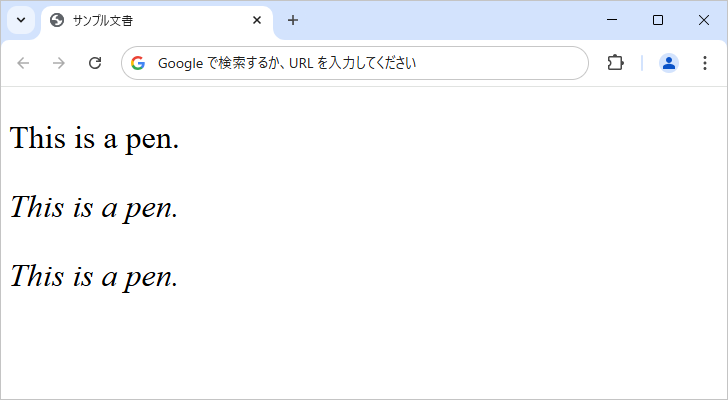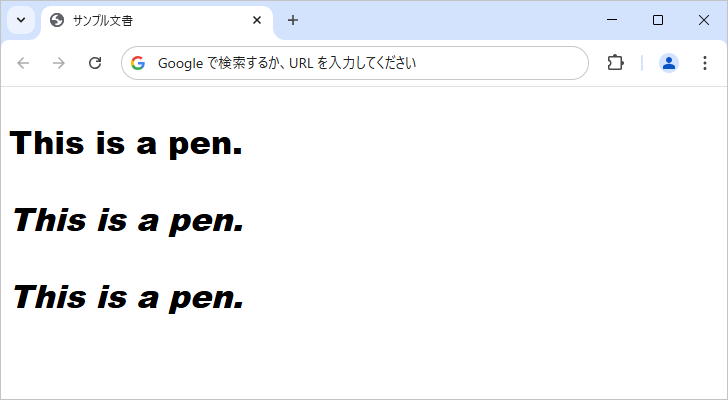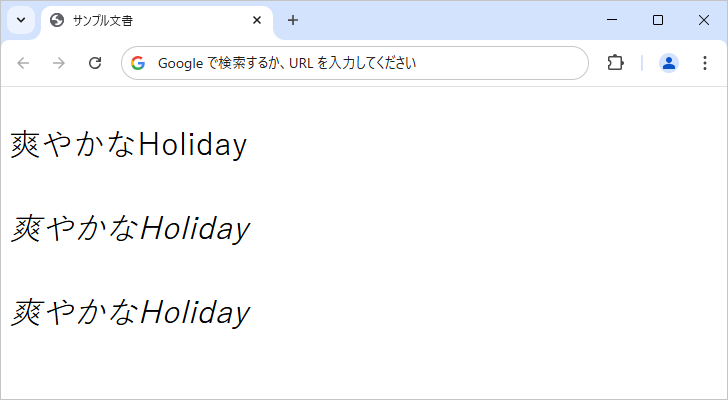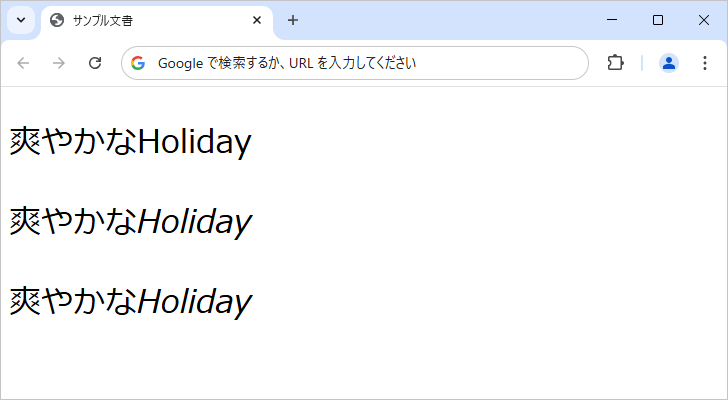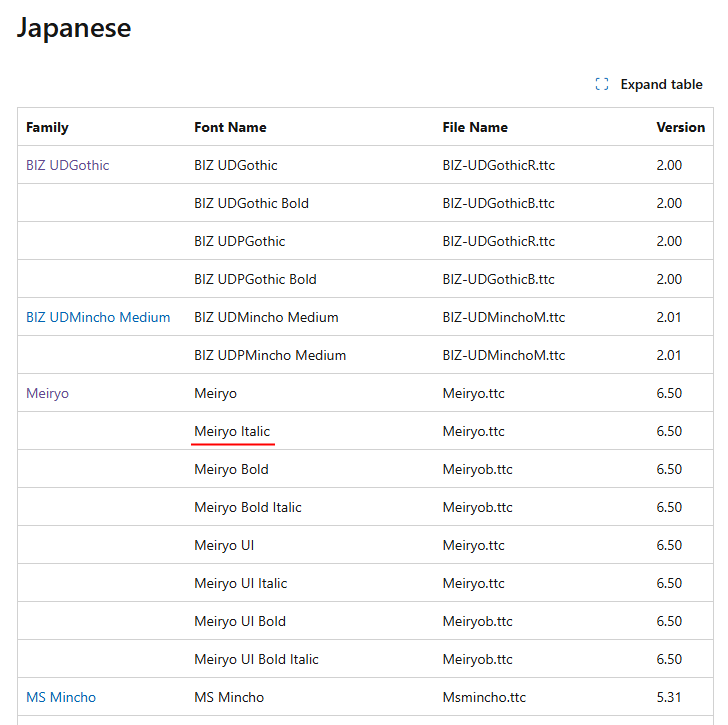
フォントのスタイルを設定する
Web ページで表示されるテキストのフォントのスタイルを設定するには、CSS の font-style プロパティを使用します。このプロパティを使うことで、テキストのスタイルを normal(標準)、 italic(イタリック体)、 oblique(斜体)のいずれかに設定できます。イタリック体( italic )は、フォントにイタリック専用のデザインがある場合に適用され、より自然なスタイルになります。一方、斜体( oblique )は、フォントにイタリックスタイルがない場合に、通常のフォントを人工的に傾けて表示します。この記事では Web ページのテキストに適用するフォントスタイルの設定方法について詳しく解説します。
font-styleを使ってフォントのスタイルを設定する
フォントのスタイルを設定するには CSS の font-style プロパティを使用します。書式は次の通りです。
スタイルには次の 3 つのいずれかを設定します。
説明
normal標準のフォントで表示
italicイタリック体のフォントで表示
oblique斜体のフォントで表示
font-style プロパティに normal を設定した場合は、標準のフォントで表示されます。 italic を設定した場合、そのフォントに イタリック体が用意されている場合は、それが適用されます。 oblique を設定した場合、そのフォントに斜体がある場合は、それが適用されます。ただし、多くのフォントは oblique スタイルを持っておらず、代わりに italic スタイルが適用されることが一般的です。対象のフォントがイタリック体も斜体も持っていない場合は、標準のフォントをブラウザが人工的に傾けた状態(擬似的な斜体)にして表示します。
なお font-style プロパティの初期値は normal です。
例えば p 要素に対してフォントのスタイルとして italic を設定する場合は次のように記述します。
簡単なテストとして次のような HTML 文書を作成しました。複数の p 要素に対してそれぞれ異なるフォントのスタイルを設定しています。
3 つの p 要素に対してそれぞれフォントのスタイルとして、 normal 、 italic 、 oblique を設定しました。 p 要素に表示されているテキストのフォントのスタイルが変更されていることが確認できます。
font-styleを使ってフォントのスタイルを設定する(1)
今回の場合、スタイルとして italic と oblique のどちらを設定した場合も同じ表示となっています。この理由は後述します。
イタリック体と斜体の違いについて
フォントのスタイルを設定するとき、 italic を設定するとフォントが持っているイタリック体、 oblique を設定するとフォントが持っている斜体、もしくは機械的に傾けたフォントが使用されます。
italic は、フォントデザインの段階で作成された専用のイタリック体を使用します。 oblique は、フォントに斜体がある場合はその斜体が適用され、ない場合はイタリック体があればイタリック体を代用し、イタリック体もない場合は標準フォントを機械的に傾けて表示します。
例えば、フォントとして Times New Roman を使用した場合、 italic を設定すると Times New Roman Italic が適用されます。一方で oblique を設定しても、 Times New Roman には Oblique スタイルが存在しないため、イタリック体が代用されます。
先ほどのサンプルではフォントとして Times New Roman を使用しました。 Times New Roman はイタリック体が用意されています。ブラウザに表示された a の文字をみてください。
イタリック体と斜体の違いについて(1)
標準のフォントとイタリック体のフォントでまったく異なる文字の形をしていることが分かります。このようにイタリック体で表示する場合は、イタリック体を使って表示します。なお Times New Roman には斜体がありません。このようにイタリック体はあるけれど斜体がない場合はイタリック体を使用して表示します。先ほどのサンプルでイタリック体と斜体が同じ表示になっていたのはこのためです。
イタリック体も斜体も用意されていない場合
イタリック体も斜体も用意されていない場合に、フォントのスタイルとして italic や oblique を設定すると、標準のフォントをブラウザが人工的に傾けた状態(擬似的な斜体)にして表示します。
例えば Windows11 の環境だと Arial Black にはイタリック体も斜体も用意されていません。そこでフォントの種類として Arial Black を設定し、スタイルとして italic や oblique を設定するとどのように表示されるのか試してみます。
Arial Black にはイタリック体も斜体も用意されていないので、標準のフォントの文字を使ってブラウザが傾けて表示しています。
イタリック体と斜体の違いについて(1)
日本語フォントの場合
日本語フォントの場合、基本的にイタリック体も斜体も用意されていません。その為、日本語フォントでフォントのスタイルとして italic や oblique を設定すると、標準のフォントを傾けて表示します。
簡単なテストとして次のような HTML 文書を作成しました。フォントの種類として Yu Gothic を設定し、複数の p 要素に対してそれぞれ異なるフォントのスタイルを設定しています。
Yu Gothic にはイタリック体も斜体も用意されていないので、標準のフォントの文字を使ってブラウザが傾けて表示しています。このように日本語のフォントであっても基本的に変わりがありません。
日本語フォントの場合(1)
ただしメイリオ(Meiryo)だけは少し挙動が異なります。
メイリオ(Meiryo)のイタリック体と斜体について
日本語フォントであっても、フォントのスタイルとして italic や oblique を設定すると文字が傾けて表示されます。ただフォントの種類としてメイリオを使用した場合、英数字については傾けて表示されますが日本語については傾けて表示されません。
簡単なテストとして次のような HTML 文書を作成しました。フォントの種類として Meiryo を設定し、複数の p 要素に対してそれぞれ異なるフォントのスタイルを設定しています。
ブラウザで表示してみると、英数字については傾けて表示されていますが、日本語についてはいずれのスタイルを設定しても変わりがありません。
メイリオ(Meiryo)のイタリック体と斜体について(1)
この理由についてはっきりした答えはまだ見つけられていないのですが、現在の環境である Windows11 には、 Meiryo だけでなく Meiryo Italic がインストールされています。(参考:Windows 11 font list)。
メイリオ(Meiryo)のイタリック体と斜体について(2)
その為、フォントのスタイルとして italic や oblique を設定した場合は、標準のフォントを傾けて表示しているのではなく Meiryo Italic を使って表示されているかと思います。そして Meiryo Italic には英語や数値の文字は用意されているけれど、日本語の漢字やひらがなについては用意されていないのではと推測しています。確認する方法も分からず根拠もないのでまったく違っている可能性もありますのでご了承ください。
Web ページのテキストに適用するフォントスタイルの設定方法について詳しく解説しました。